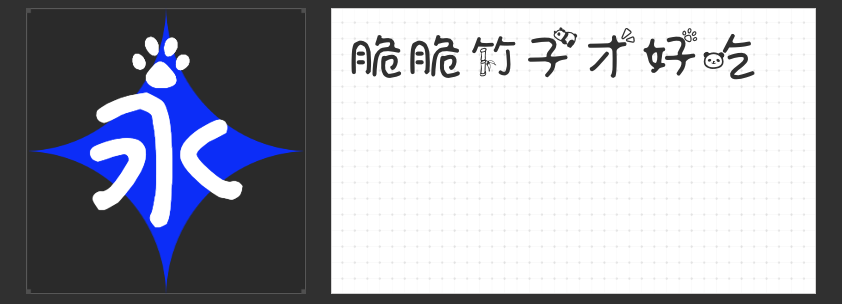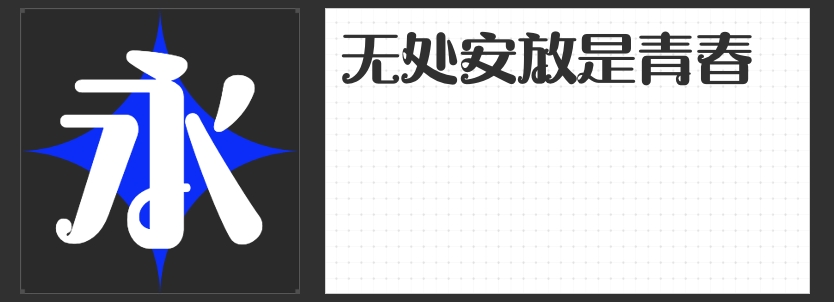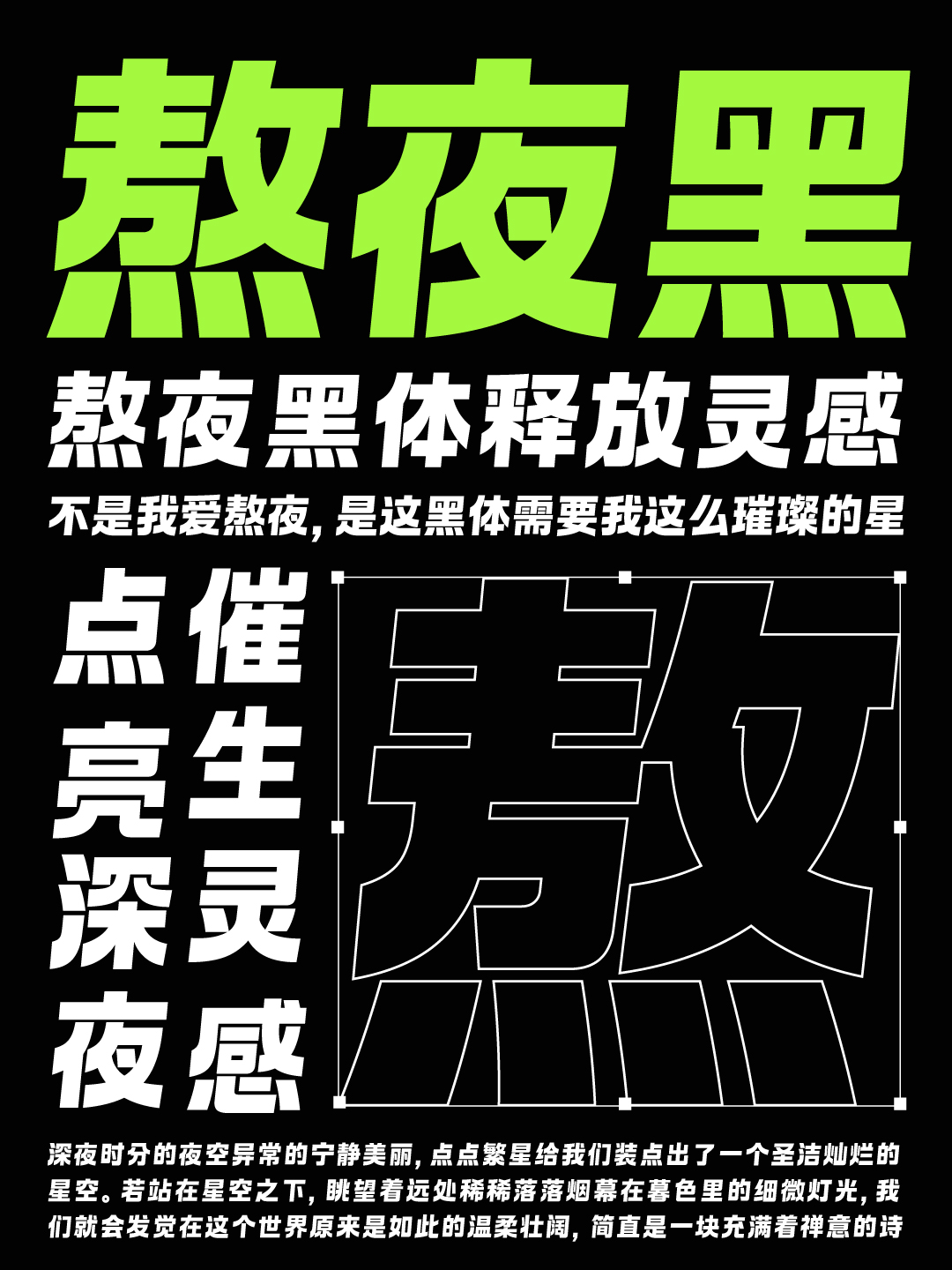
四款字体激发文具设计灵感
在文具设计领域,字体的选择往往决定了产品的第一印象和整体风格。一个优秀的字体不仅可以增加文具的美观度,还能传递出品牌想要表达的情感与文化内涵。以下是四款特别适合用于文具设计的字体推荐,它们各具特色,能够满足不同风格需求。
1. MyFont求假期简 细体
MyFont求假期简 细体是一款轻盈且充满活力的字体,它以其简洁流畅的线条和优雅的字形脱颖而出。这款字体非常适合用于笔记本封面、便签纸或者日记本的设计中,给人以轻松愉悦的感觉,仿佛每一次落笔都能唤起人们对美好假期的向往。其细体的设计更添一份精致感,让文具产品看起来更加高雅而不失亲和力。
2. 字圈也字小熊猫
如果你的目标消费群体中有儿童或追求童心未泯的年轻人,那么字圈也字小熊猫绝对是一个不可多得的好选择。这款字体以其可爱的熊猫元素和圆润的笔触闻名,能够在第一时间抓住人们的眼球。无论是用于设计学生用品还是办公室里的创意文具,字圈也字小熊猫都能为产品增添一抹温馨的色彩,让人感受到无尽的欢乐与温暖。
3. 字圈也字熬夜黑
针对那些夜猫子设计师或是喜欢在夜晚寻找灵感的创作者们,字圈也字熬夜黑提供了完美的解决方案。这款字体采用了较为粗重的笔画设计,但并不显得笨重,反而有一种强烈的现代感。它适合用于笔记本、记事本等需要强调力量与决心的文具设计中,能够激励使用者在忙碌的工作生活中找到属于自己的节奏。
4. 励字摩登圆简
对于追求简约风格的专业人士而言,励字摩登圆简无疑是他们理想中的字体。它融合了现代设计理念与传统的书写美感,既保持了清晰易读的特点,又不失时尚感。无论是作为办公文件夹上的标签还是会议记录本的标题,励字摩登圆简都能展现出现代职场人的专业态度与审美品味。
在选择字体时,不仅要考虑字体本身的美学价值,还要考虑到它与目标市场文化的契合度。上述四款字体各有千秋,能够满足不同类型文具设计的需求。无论是追求优雅简约还是趣味横生的设计风格,这些字体都将为您的创意提供强有力的支持。